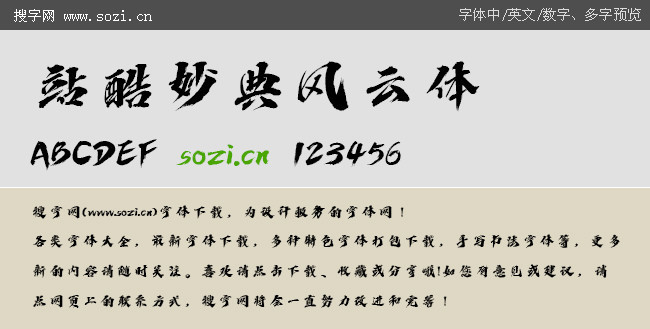
站酷妙典風(fēng)云體
搜字網(wǎng)給大家提供一款站酷妙典風(fēng)云體中文書法字體下載,站酷妙典風(fēng)云體是一款風(fēng)格硬朗且具有張力的手寫類毛筆字體,此款字體筆畫特點(diǎn)運(yùn)用在撇捺勾轉(zhuǎn)折之間,適當(dāng)?shù)目菽w白、粗細(xì)對(duì)比的筆畫和帶有力量感的運(yùn)筆方式,使字形在視覺(jué)上有更好的沖擊力,在活動(dòng)海報(bào)、影視綜藝類等大標(biāo)題字的設(shè)計(jì)上將會(huì)有更好的視覺(jué)效果。(本字體為個(gè)人非商用版,如需要商用請(qǐng)聯(lián)系作者購(gòu)買版權(quán))